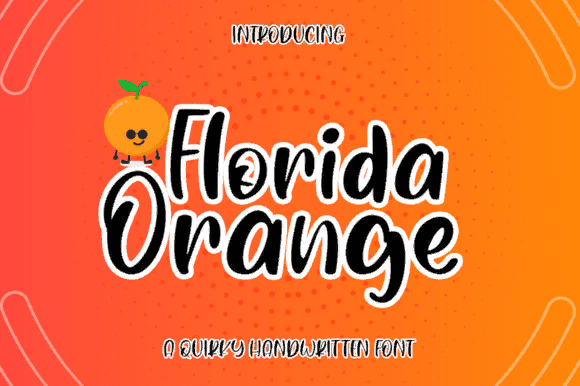
Название: Florida Orange Font (2021)
Florida Orange - это милый и причудливый шрифт.
Он добавит невероятно радостный штрих в ваши проекты.
Добавьте этот красивый шрифт к каждой из своих творческих идей и заметите, как он их выделяет!